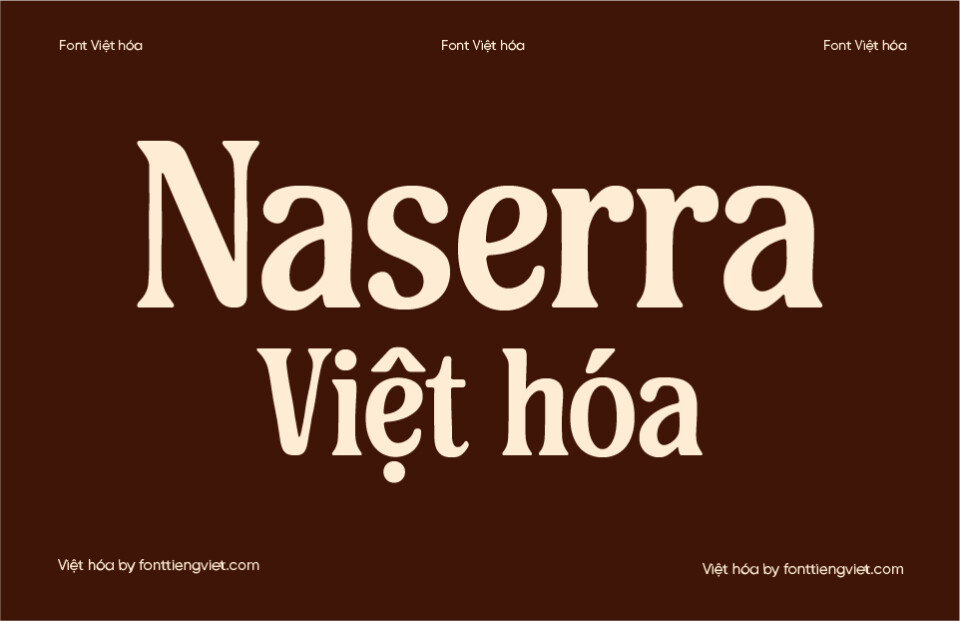
Font Việt hóa 1FTV Naserra – Đẳng cấp tinh tế cho mọi thiết kế đồ họa
Giới thiệu về Font Việt hóa 1FTV Naserra
Trong thế giới sáng tạo, việc lựa chọn một Font Chữ phù hợp đóng vai trò quyết định đến sự thành công của một tác phẩm. Font Việt hóa 1FTV Naserra nổi lên như một giải pháp hoàn hảo cho những ai đang tìm kiếm sự kết hợp giữa nét hiện đại và phong cách cổ điển đầy lôi cuốn. Đây là bộ phông chữ được tinh chỉnh kỹ lưỡng, giúp người dùng dễ dàng thể hiện nội dung tiếng Việt mà không lo lỗi hiển thị dấu hay khoảng cách ký tự. Với đường nét thanh mảnh nhưng chắc chắn, Naserra mang lại cảm giác chuyên nghiệp và vô cùng sang trọng.
Tại sao nên chọn Font Việt hóa 1FTV Naserra cho dự án của bạn?
Bộ Font Việt hóa 1FTV Naserra sở hữu bộ ký tự đa dạng, phù hợp với nhiều mục đích khác nhau từ thiết kế tiêu đề sách, thiệp mời đến bộ nhận diện thương hiệu. Đặc biệt, đối với các bạn học sinh và giáo viên, phông chữ này giúp các bài thuyết trình trở nên sinh động và bắt mắt hơn bao giờ hết. Nhờ cấu trúc hình học cân đối, Naserra đảm bảo tính dễ đọc trên cả thiết kế in ấn lẫn hiển thị kỹ thuật số.
Cách ứng dụng Font Việt hóa 1FTV Naserra hiệu quả nhất
Để tối ưu hóa vẻ đẹp của Naserra, bạn nên kết hợp nó với các màu sắc trung tính hoặc phong cách tối giản. Font chữ này hoạt động cực kỳ tốt khi được sử dụng làm headline cho các trang web thời trang hoặc làm nội dung chính trong các poster sự kiện trường học. Việc tải và cài đặt bộ phông này vô cùng đơn giản, giúp bạn tiết kiệm thời gian mà vẫn đạt được hiệu quả thẩm mỹ cao nhất cho sản phẩm của mình.
Kết luận về bộ font chữ độc đáo